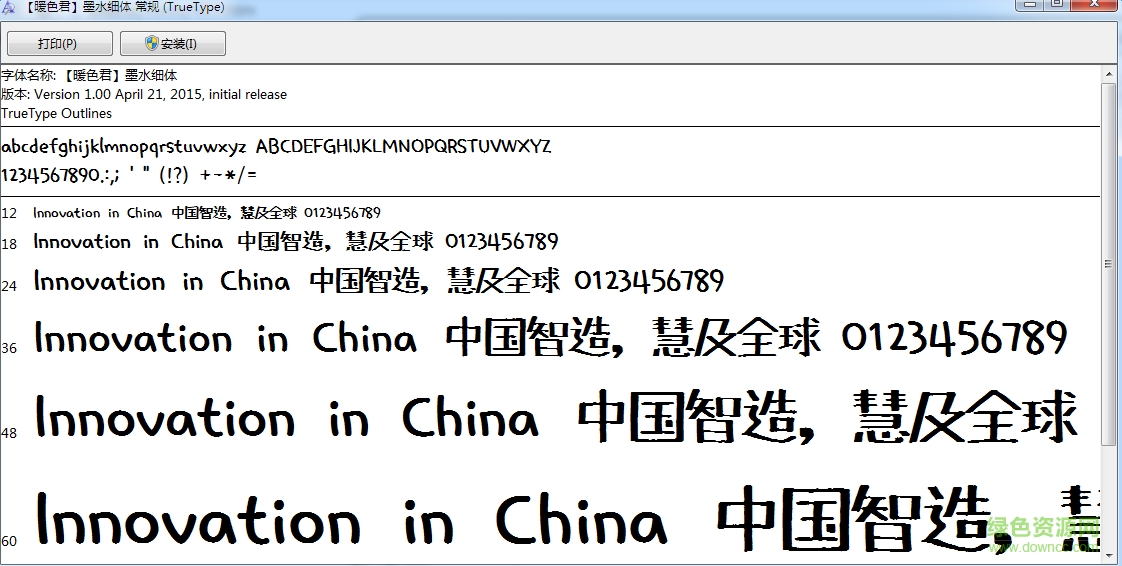
暖色君墨水細(xì)體字體是一款用于電腦上的細(xì)體字體,字體非常的有特色,該字體風(fēng)格簡(jiǎn)約,結(jié)構(gòu)簡(jiǎn)約清新,辨識(shí)度高,整體效果非常出色,并擁有完整的字庫(kù),非常適合用來(lái)創(chuàng)作,有需要?dú)g迎下載!
暖色君墨水細(xì)體是一款簡(jiǎn)潔大氣的win細(xì)體,此款字體線條較細(xì),清醒爽目,擁有完整的字庫(kù),結(jié)構(gòu)簡(jiǎn)潔,易讀性強(qiáng),安裝簡(jiǎn)單方便,使用范圍非常廣泛!